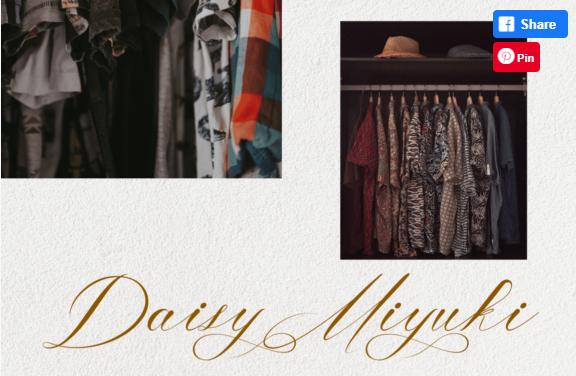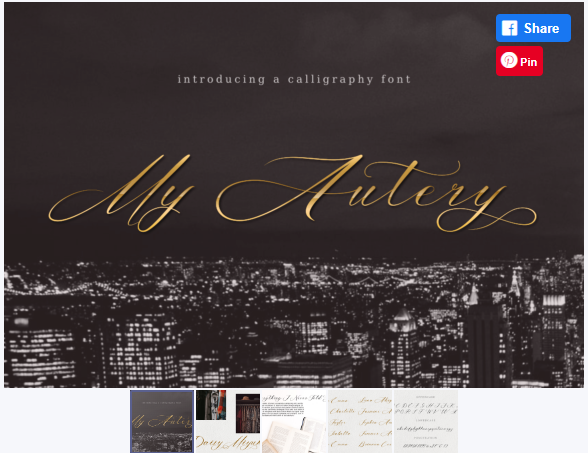
[Creativefabrica] My Autery Font (The Grateful Studio)
My Autery - это изящный и уникальный шрифт. Добавьте этот романтичный и милый на вид шрифт в каждое из ваших любовных писем, свадебных приглашений или любимых дизайнерских идей, и вы будете поражены результатом. Добавьте этот романтичный и милый на вид шрифт в каждое из ваших любовных писем, свадебных приглашений или любимых дизайнерских идей, и вы будете поражены результатом.